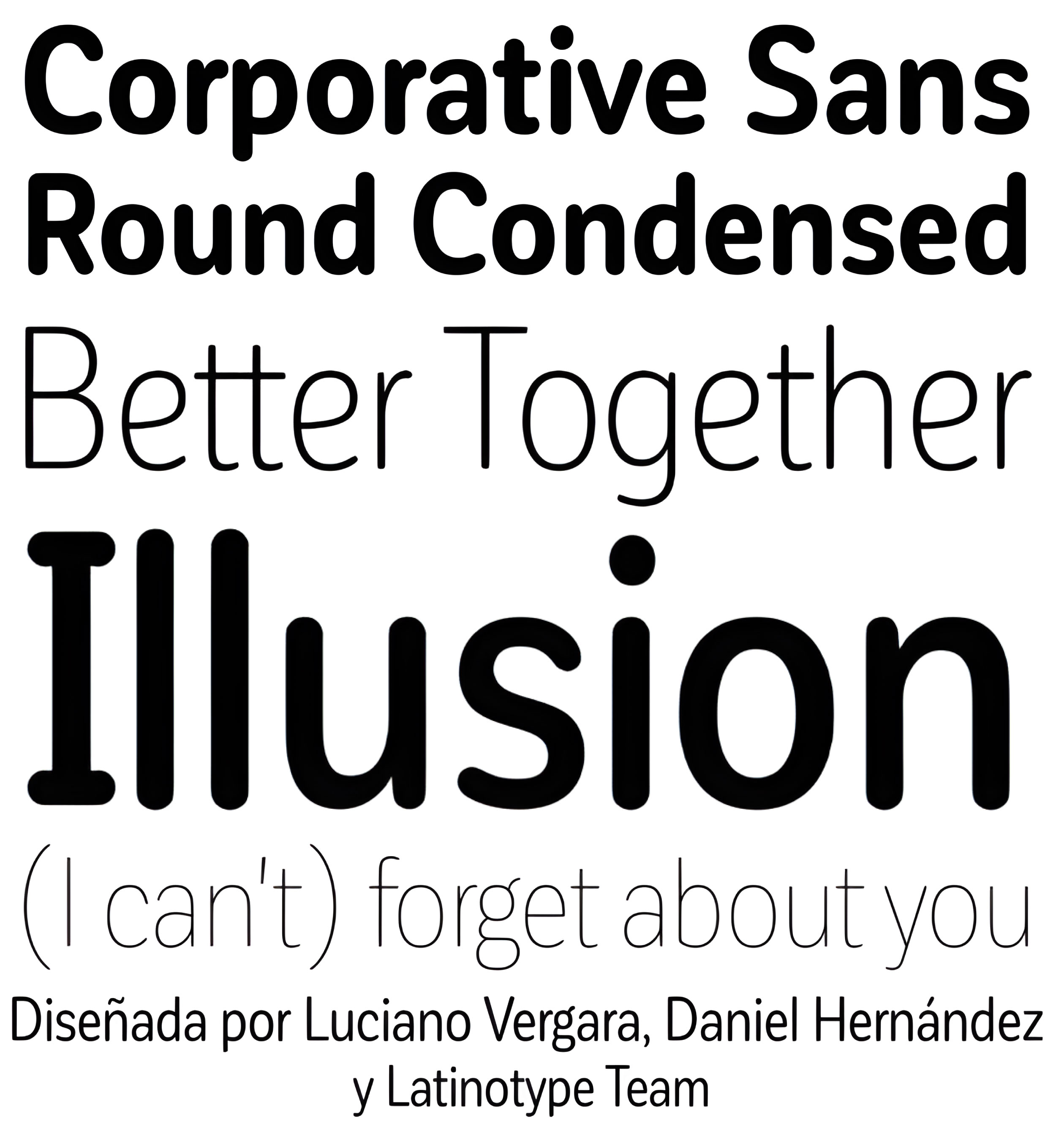
| Año | 2016 |
| Créditos | Luciano Vergara, Daniel Hernández |
| Descripción | Corporative Sans Rounded Condensed es la versión reducida de Corporative Sans Rounded que ofrece un alto rendimiento cuando se utiliza para texto, lo que la convierte en la combinación perfecta para Andes redondeados. La fuente funciona bien tanto en tamaños de pantalla como pequeños. Corporative Sans Rounded Condensed es la elección perfecta para logotipos, carteles, letreros, marcas, envases, etc. Corporative Sans Rounded Condensed incluye el conjunto estándar de 350 caracteres de Latinotype, lo que permite utilizar la fuente en 128 idiomas diferentes. Corporative Sans Rounded Condensed ofrece a los usuarios una amplia gama de caracteres y pesos para cada proyecto. Combinando distintas variantes, los diseñadores pueden conseguir los mejores resultados. La familia consta de 32 fuentes: una familia básica que incluye 8 pesos más cursiva y una familia alternativa de 8 pesos con cursiva a juego también. Corporative Sans Rounded Condensed fue creada por Latinotype Team y desarrollada por Elizabeth Hernández y Rodrigo Fuenzalida, bajo la supervisión de Luciano Vergara y Daniel Hernández. |
| Familia(s) | Corporative Sans Rounded Condensed |
| Estilos | 31 |
| Glifos | mayor que 1000 |
| Estudio | Latinotype |